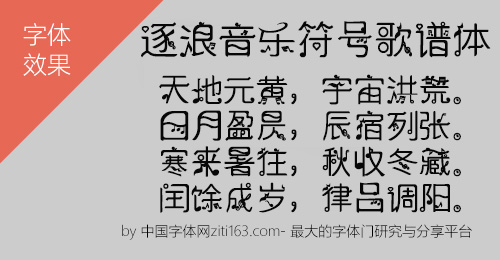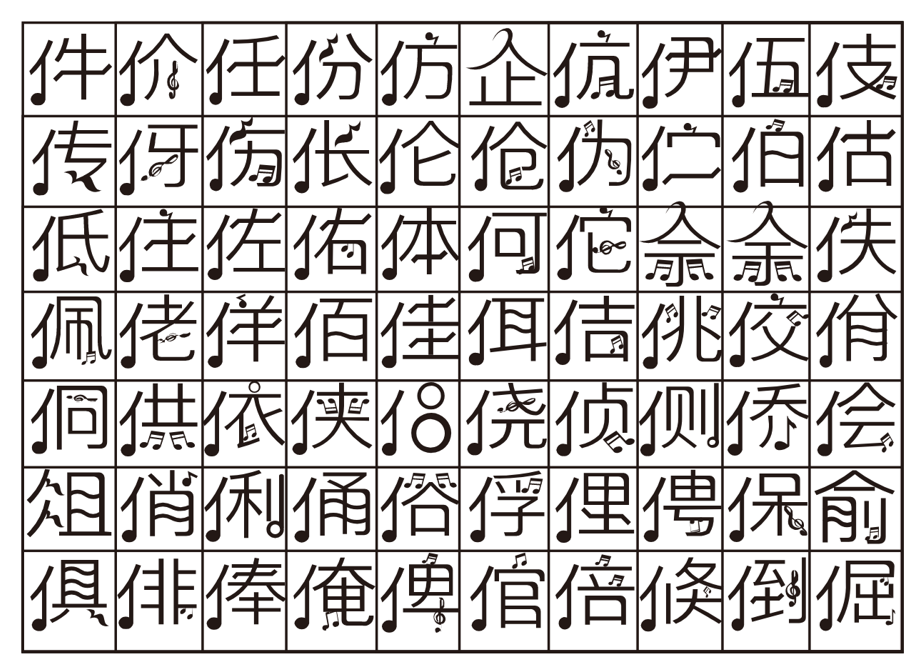
逐浪音乐符号歌谱体.otf是由逐浪字库出品的一款电脑字体,也可以用于手机字体。逐浪字库Zoomla!Fonts是由北京出海软件科技有限公司专注打造的中文精品字库,汇聚逐浪CMS团队在软件和基础数据多领域的智慧结晶,以汉字文化为基石,广泛应用于政府、出版、报业、密码、军工等场景,是目前业界唯一由技术编程团队构建的中文全场景字库,不趋媚西日、不一孔复古、开放严谨,完善的理念和技术恢宏文化。